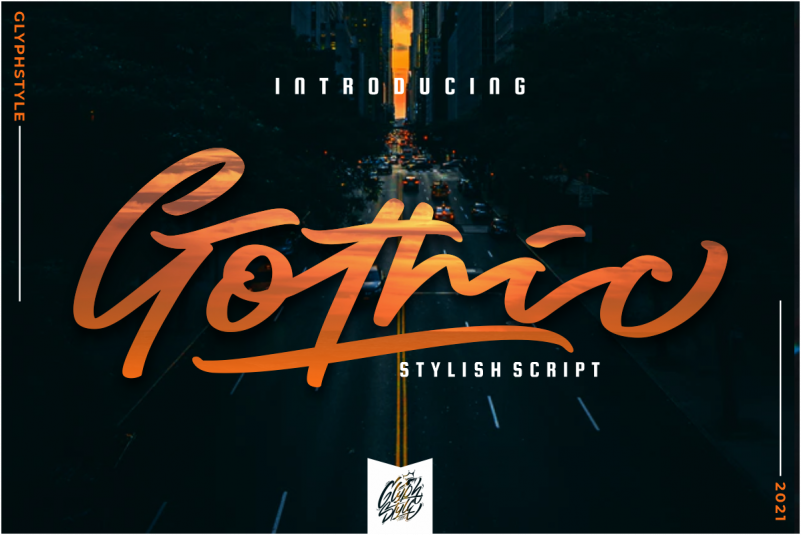
Aqui está uma descrição envolvente e natural para a página de download da fonte ‘Gothic Script Font’, seguindo as instruções fornecidas: Esta é uma fonte script stylizada, com uma variedade extensa de caracteres. Perfeita tanto para estilos minimalistas quanto para trabalhos mais elaborados, essa fonte possui um estilo robusto e moderno, ideal para aplicativos como identidade visual corporativa. Com seu design clean e elegante, a Gothic se destaca por sua simplicidade e força, tornando-a uma opção ótima para projetos que buscam uma aparição fresca e contemporânea. Seja em títulos de página ou em textos interiores, a fonte ‘Gothic Script Font’ oferece um toque moderno que irá destacar seu projeto. Combinada com a tipografia clara da designer GlyphStyle, a Gotheis pode transformar qualquer design em algo único e memorável.